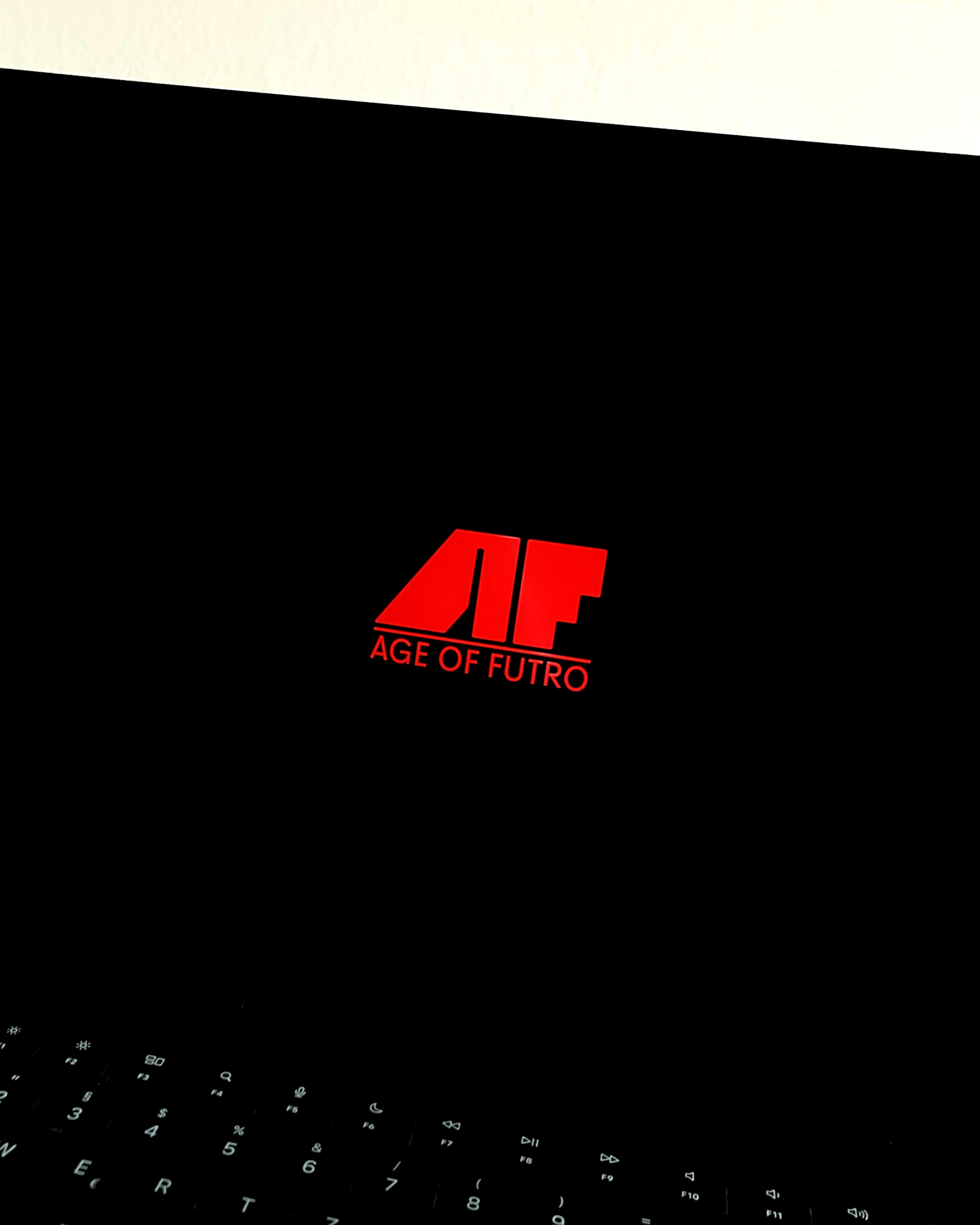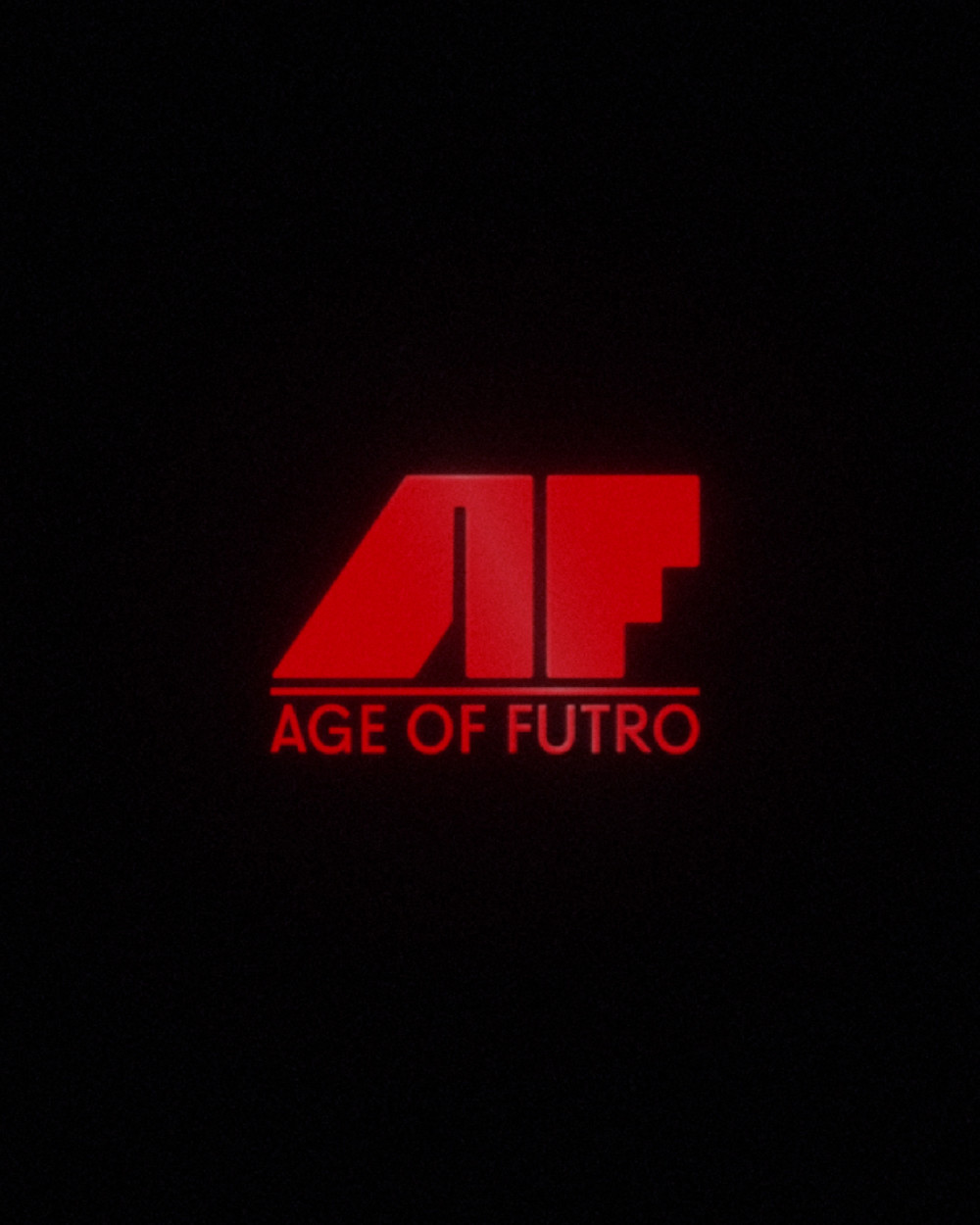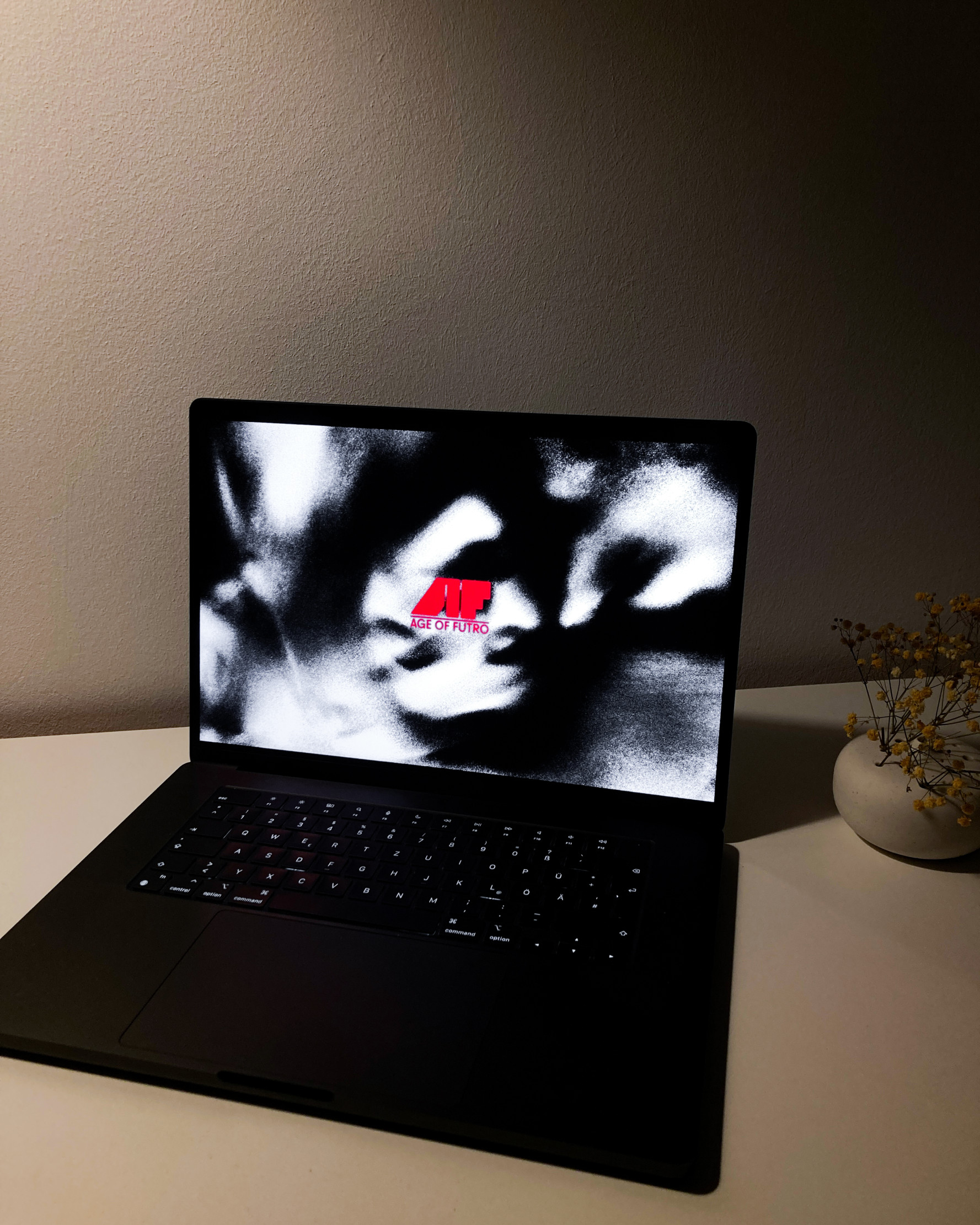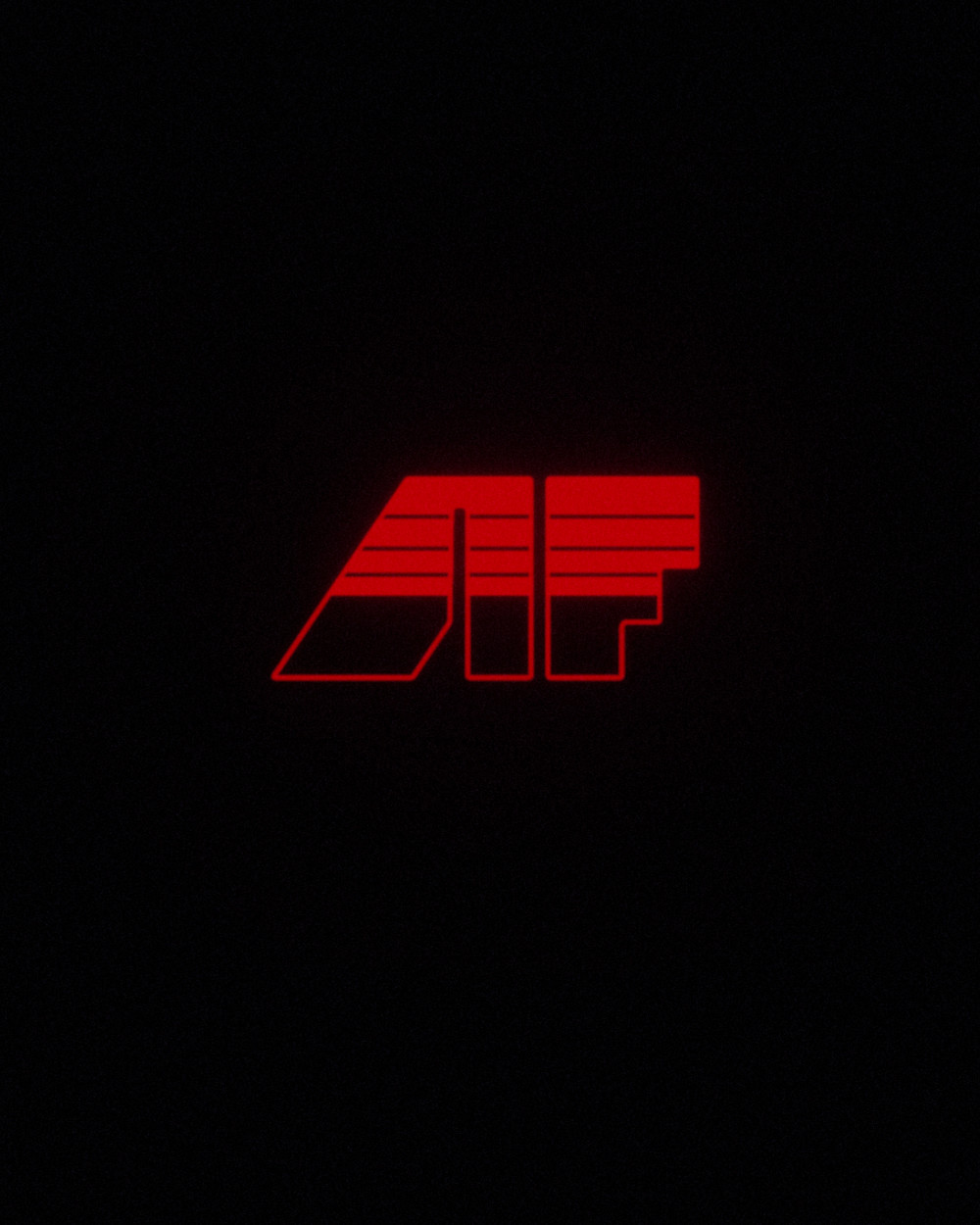
Age of Futro
Logodesign für die Produktionsfirma Age of Futro von Anil Jacob Kunnel.
Mit der Gestaltung des Logos beziehen wir uns auf die Erscheinungsbilder der verschiedenen Filmproduktionsfirmen aus den 80er Jahren und erzeugen so einen retrofuturistischen, coolen Look. Durch die rote Farbwahl vermittelt das Logo zudem eine gewisse Düsternis und Bedrohlichkeit.
Schrift: L10 von OrType